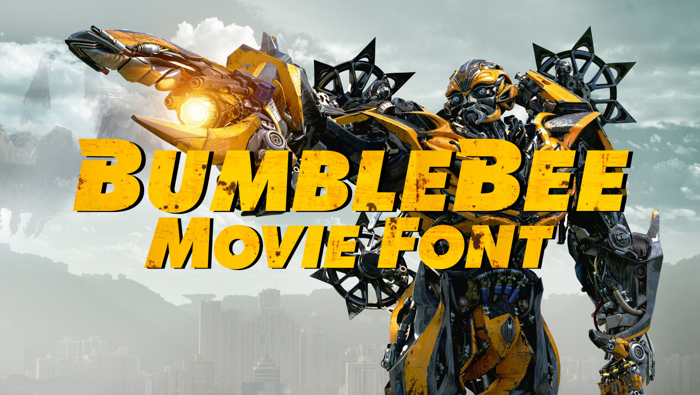
BumbleBeee Font
A Font based from the movie: BUMBLEBEE
Una fuente basada en la película: BUMBLEBEE
¡Hola, aquí aparece con triple "e" pero cuando lo descargas y lo instalas te aparece 'BumbleBee!.
Sólo que al crear la fuente le puse la tercera 'e' y me equivoque, pero ya esta editada y actualizada aquí en FontSpace para que sea 'BumbleBee' y no BumbleBeee'